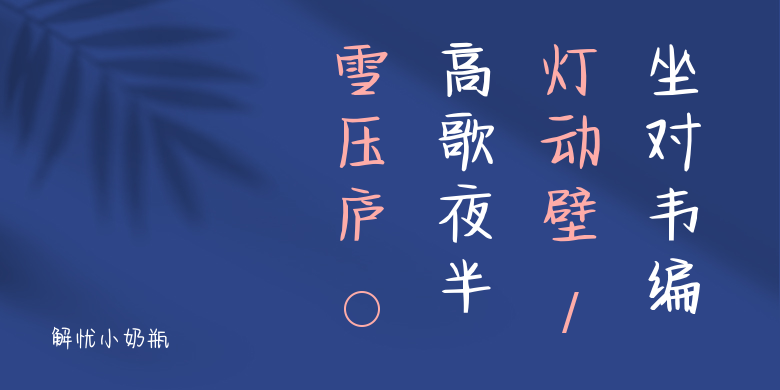
解忧小奶瓶
解忧小奶瓶,这款字体结构工整、笔画清晰,兼顾美观与易读性,适用于标题、正文、海报、包装、LOGO 等多种场景。字形优雅稳定,风格百搭耐看,适配日常排版与创意设计,让文字呈现更舒适、更具质感。解忧小奶瓶一笔一画,皆是细节,以均衡的比例、流畅的线条打造舒适视觉体验,字形端正大气,风格简约现代。无论是商业设计、品牌宣传还是日常排版,都能轻松驾驭,让文字更有格调与力量。解忧小奶瓶字体下载。